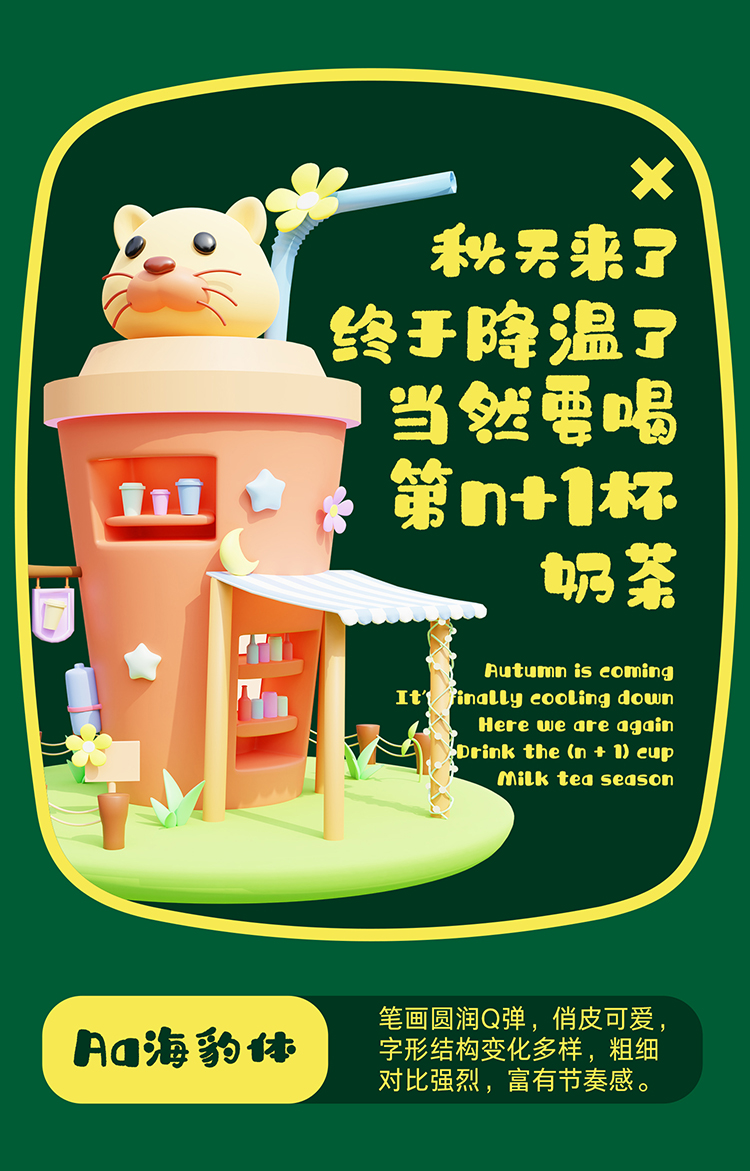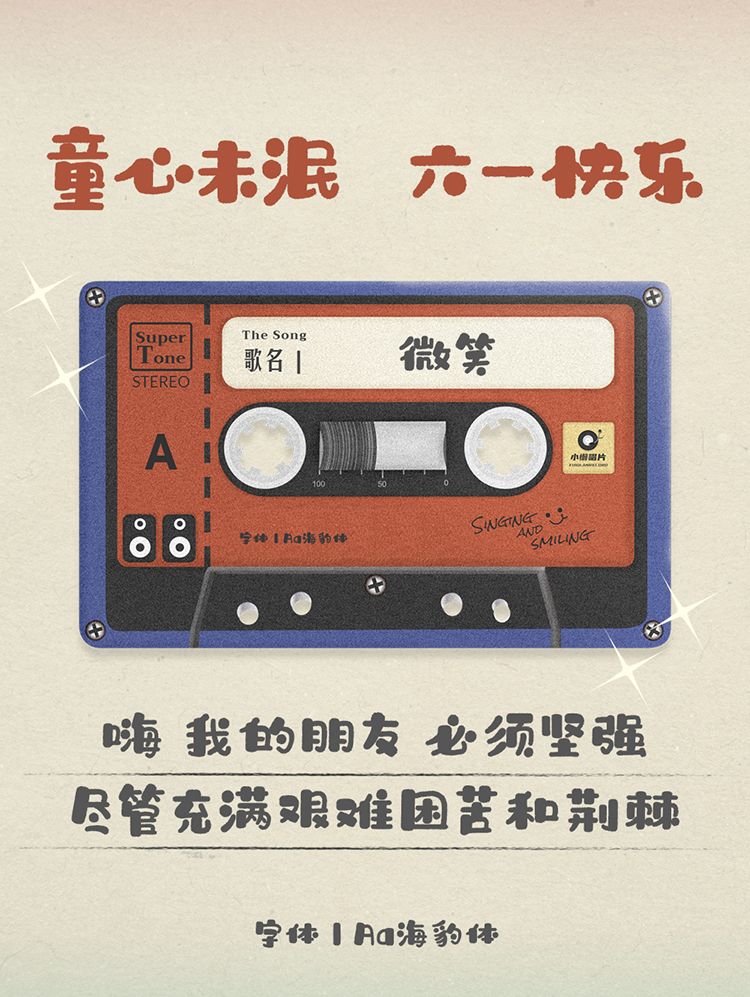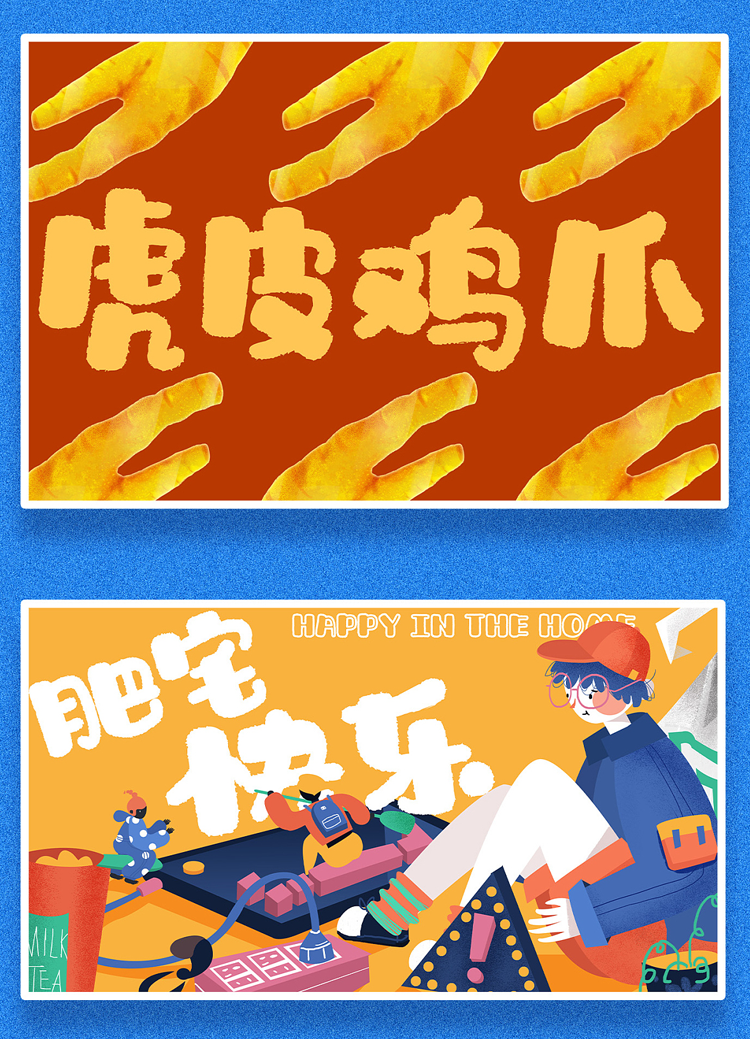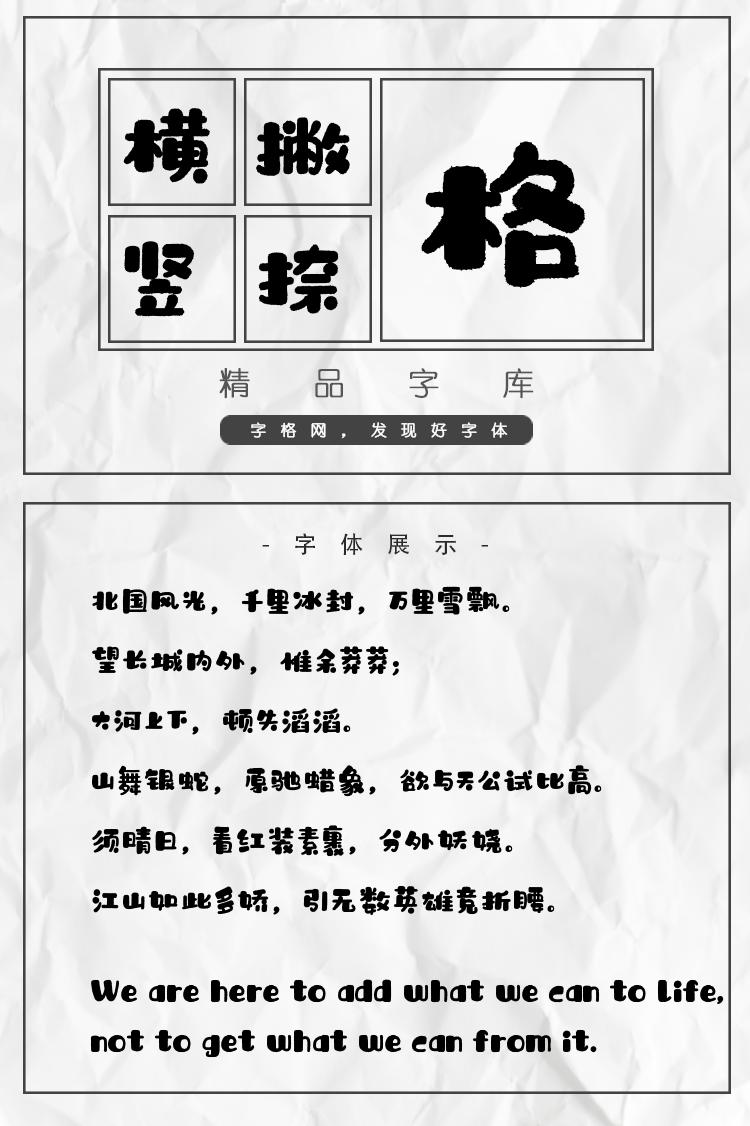
Aa海豹体
字体说明:Aa海豹体字体是一款可商用的毛笔书法,英文手写,手写体字体,该字体包含6763个中文、字母、符号和数字,具有充满力量、大气、豪放、稳重、手写风、古典 的风格,可以满足您设计上的各种需求,该字体主要用于电商、广告、视频影视、海报企宣、书籍 等场景, 您不但可以在字格网下载Aa海豹体,同时还有众多毛笔书法字体、创意字体等可供选择!